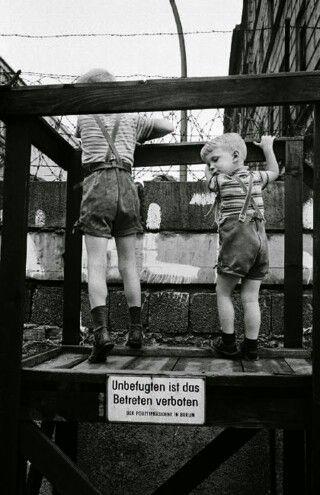
Schrift an Berliner Mauer
Hallo liebe Leute, könnt ihr mir sagen, welche Schrift das ist? Sie ist relativ eng und das kleine b und d sind speziell. Danke!
Sollten Dir aber auch alternative Font-Entwürfe unserer Zeit genügen, dann könnten diese vielleicht etwas sein:
(Schade nur, dass sich das einfache a offenbar nicht einzeln über Opentype ansprechen lässt, sondern auch das komplexere t mit aktiviert wird)